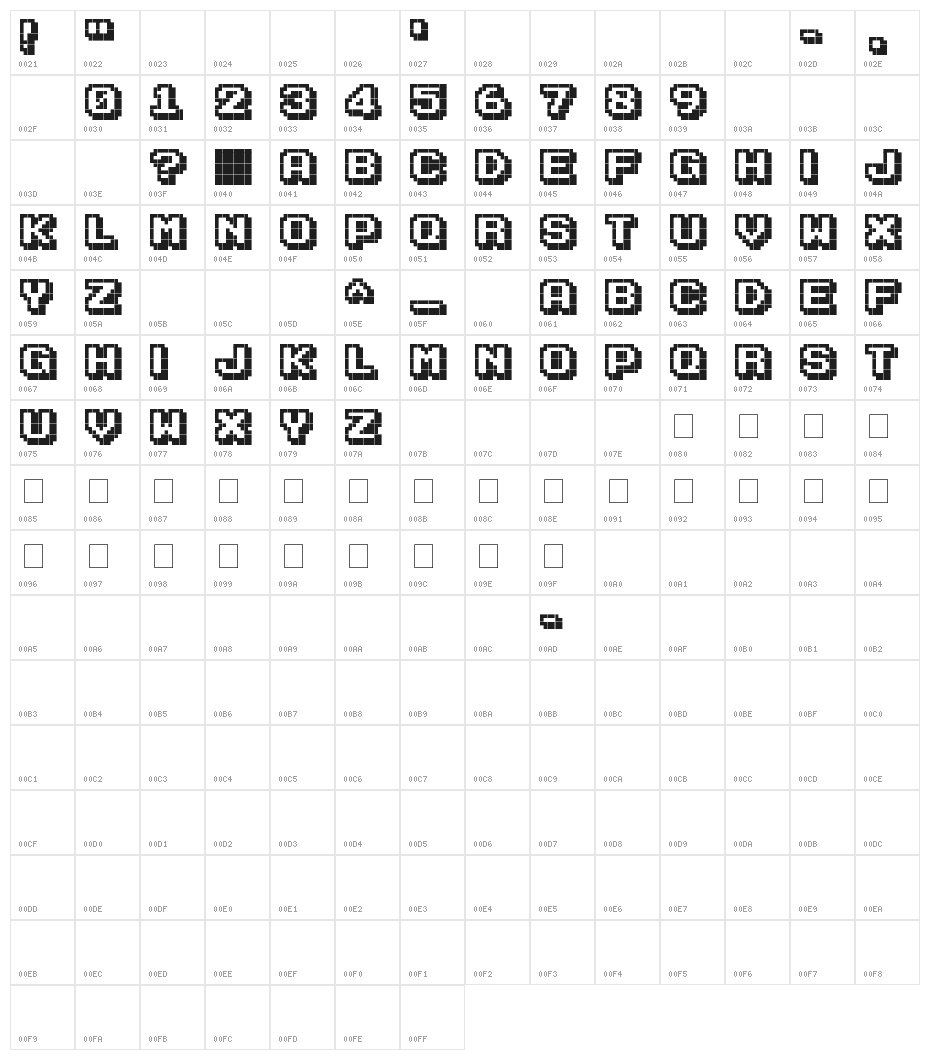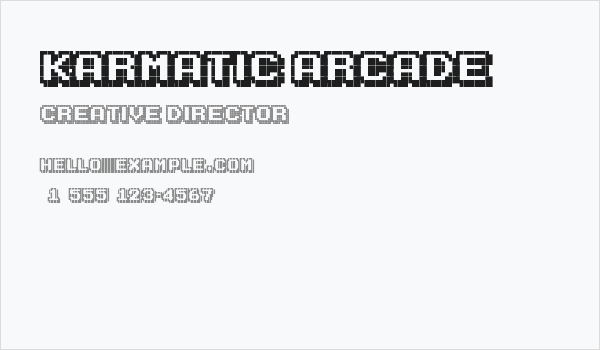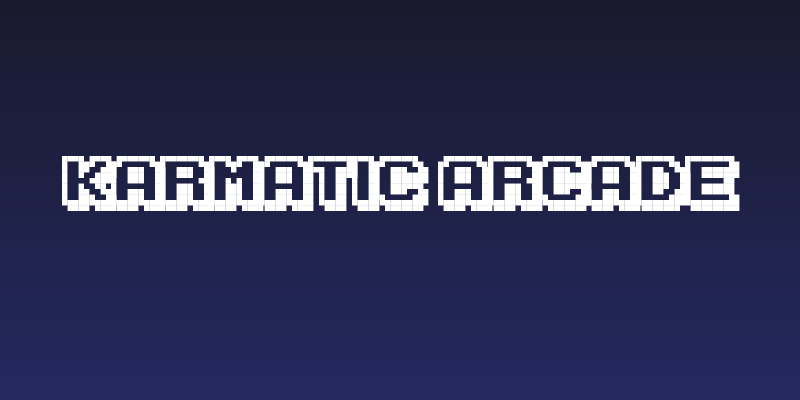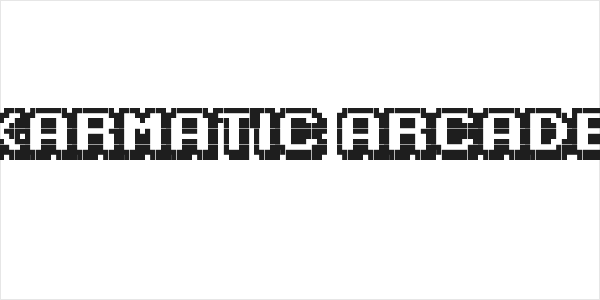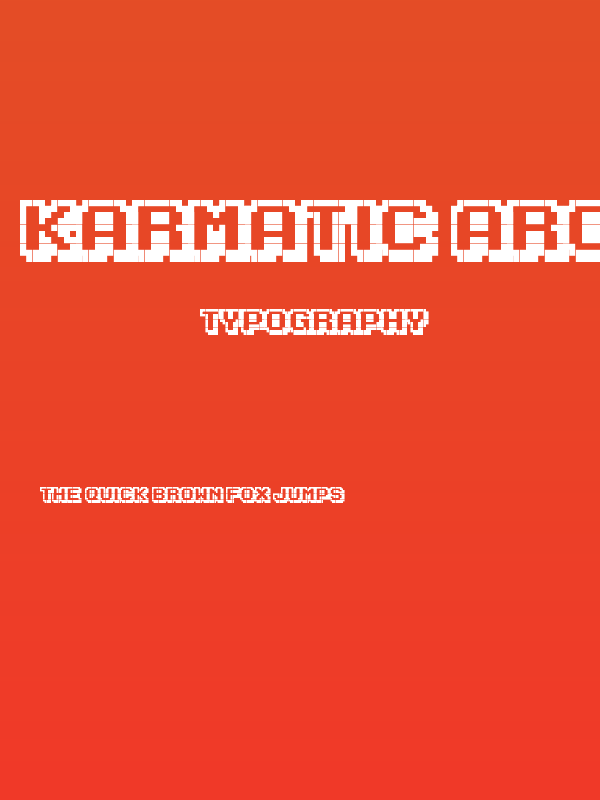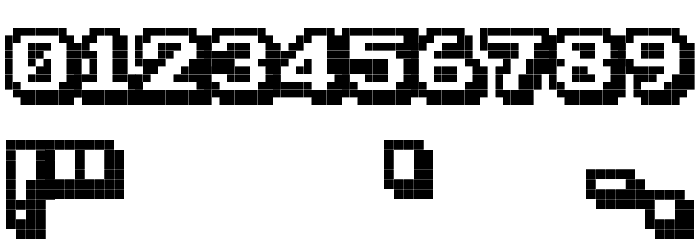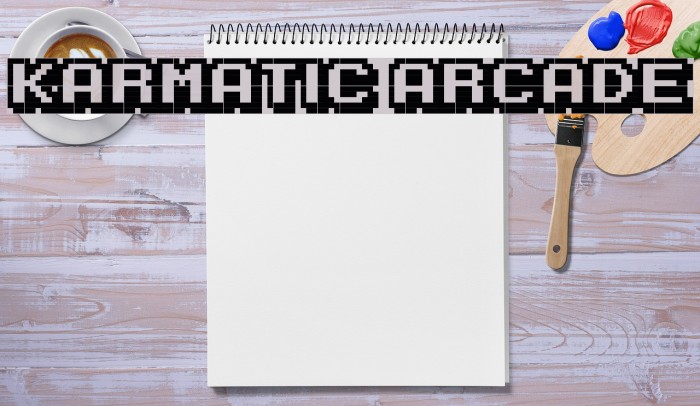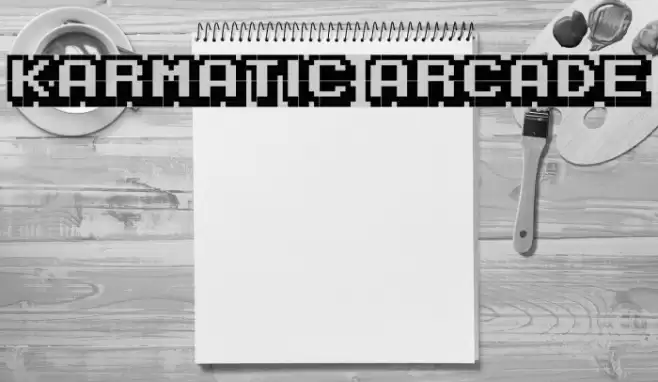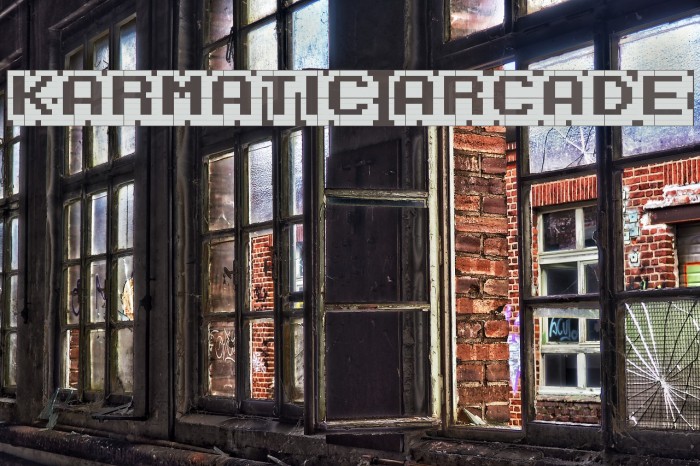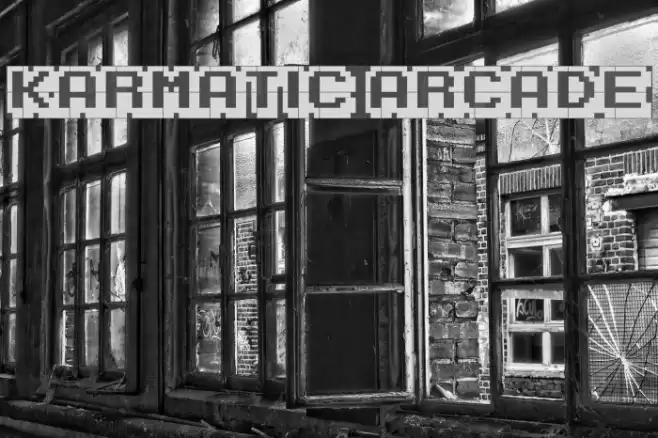
Karmatic Arcade Font
| Estilo general | Vintage |
| Caso de uso | Headlines, Logos, Digital Art |
| Proyectos propuestos | Ideal for retro-themed video games, digital art projects, and nostalgic branding. |